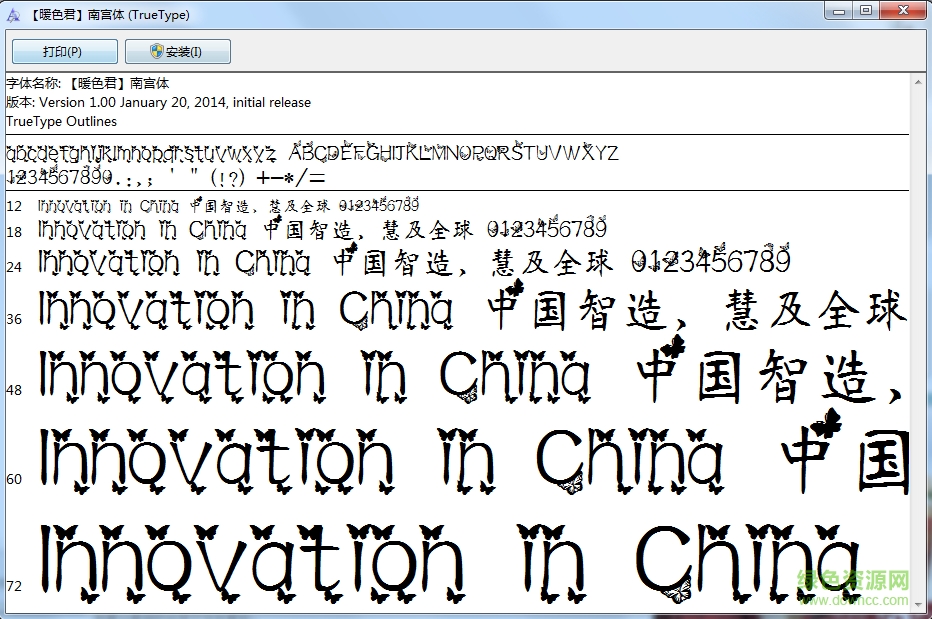
南辭遇蝶也叫暖色君南宮體,因字里行間用蝴蝶來點(diǎn)綴而命名,感受浪漫的花間氣息、繞指的蝴蝶肆意飛舞,更多浪漫藝術(shù)字體,盡在綠色資源網(wǎng)等你體驗(yàn)!
南辭遇蝶的真正名稱為暖色君南宮體,是暖色君系列字體之一,因其蝴蝶形點(diǎn)綴而得名,為你帶來春之浪漫、蝶舞花間的愉悅氣息!